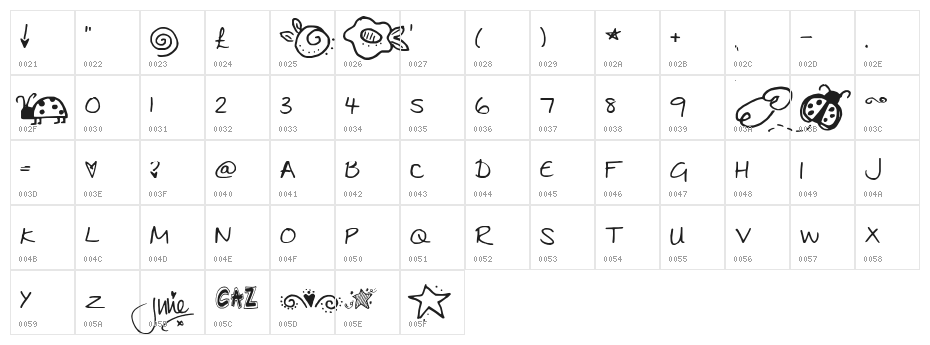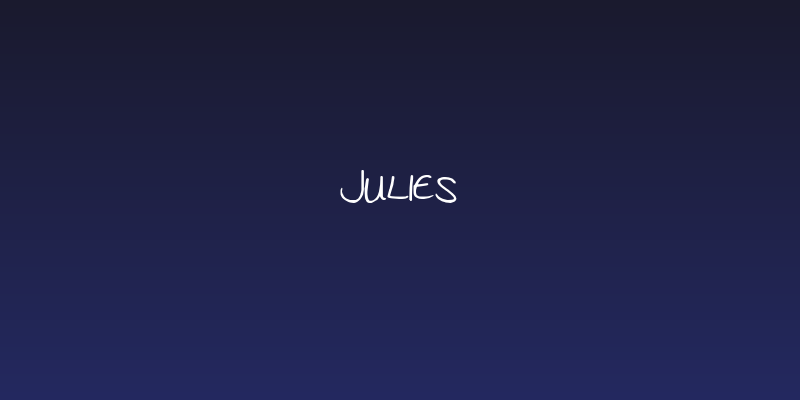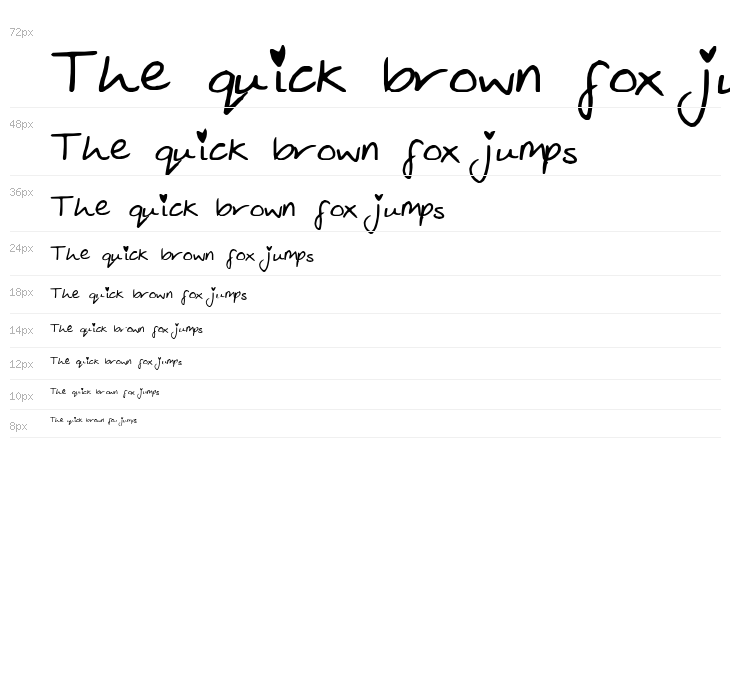
Julies Font
| Caso d'uso | Logos, Headlines, Informal Text |
| Progetti proposti | Ideal for greeting cards, children's books, playful branding, and personal invitations. |